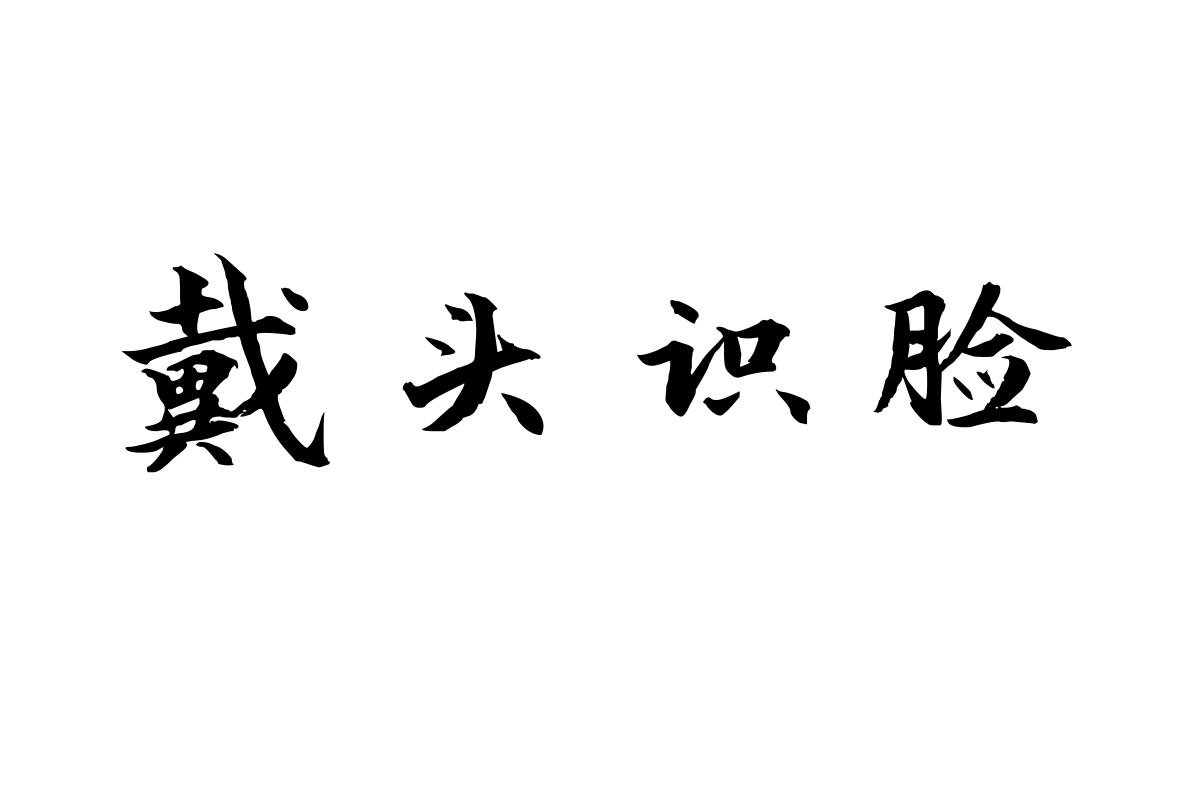
三极文明劲楷是一种汉字字体,由北京三极文明科技有限公司设计。该字体以其独特的风格和美感而受到广泛关注。
三极文明劲楷采用了现代设计理念,将传统书法与现代平面设计相结合,创造出一种既具有传统韵味又不失现代感的字体。其笔画流畅、结构紧凑,给人一种简洁明快的感觉。
这种字体适用于各种场合,如广告、包装、出版物等。无论是商业还是艺术领域,三极文明劲楷都能够满足不同用户的需求。